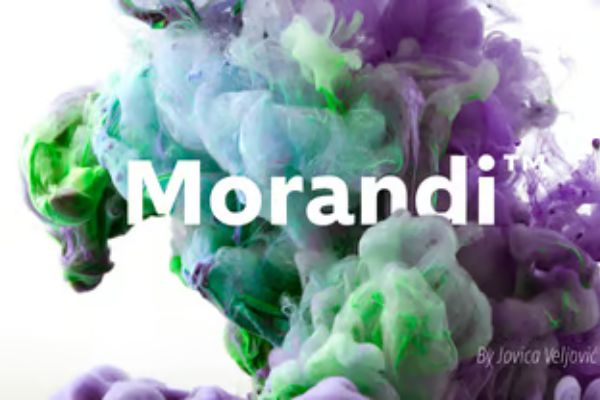
Morandi™ Pro Condensed Light
Morandi 是第一个商业无衬线字体,它的每个细节都经过精心打磨,不仅外观优雅,而且设计高效清晰。Morandi 足以在印刷和数字环境中良好应用,其突出的标点符号可以提高屏幕上的可读性,既实用又美观。它包含 800 多个带有 OpenType 功能的字形,并包含大量跨国字符集。